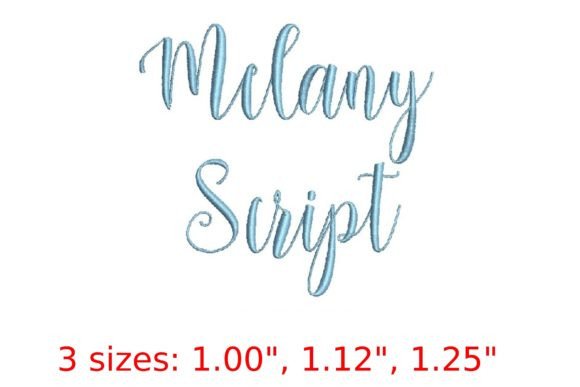
Melany Script Embroidery Font
Melany Script Embroidery Font — це елегантний, ручно створений шрифт у стилі PES-скрипт, спеціально розроблений для машинної вишивки. Його плавні, витончені лінії та природні з’єднання літер імітують справжні рукописні написи, що робить його ідеальним вибором для вишивальних проектів, де важлива особистісна, романтична або класична естетика — від весільних прикрас до персоналізованих подарунків та брендування текстилю.
Якість збірки та технічні деталі
Для кого найкраще підходить цей продукт?
Цей шрифт ідеально підійде професійним вишивальникам, які працюють з комерційними замовленнями (весільні аксесуари, іменні рушники, дитячі речі), а також хобі-майстрам, що використовують домашні вишивальні машини Brother, Janome або Bernina. Також він стане в нагоді дизайнерам, які створюють цифрові шаблони для продажу на Etsy або Creative Market — завдяки унікальній, нестандартній структурі Melany легко відрізнити від масових скриптів.
Як це порівнюється з конкурентами
На відміну від популярних універсальних скриптів, таких як KG Primary Penmanship або Great Vibes PES, Melany має вищі параметри адаптації до вишивки: менше перехресних ниток, більш гнучкі криві та вбудовану компенсацію для стискання ниток. Порівняно з безкоштовними PES-шрифтами, Melany демонструє значно кращу стабільність при автоматичному масштабуванні та не вимагає ручного редагування контурів у Wilcom или Pulse — всі елементи готові до використання 'з коробки'.